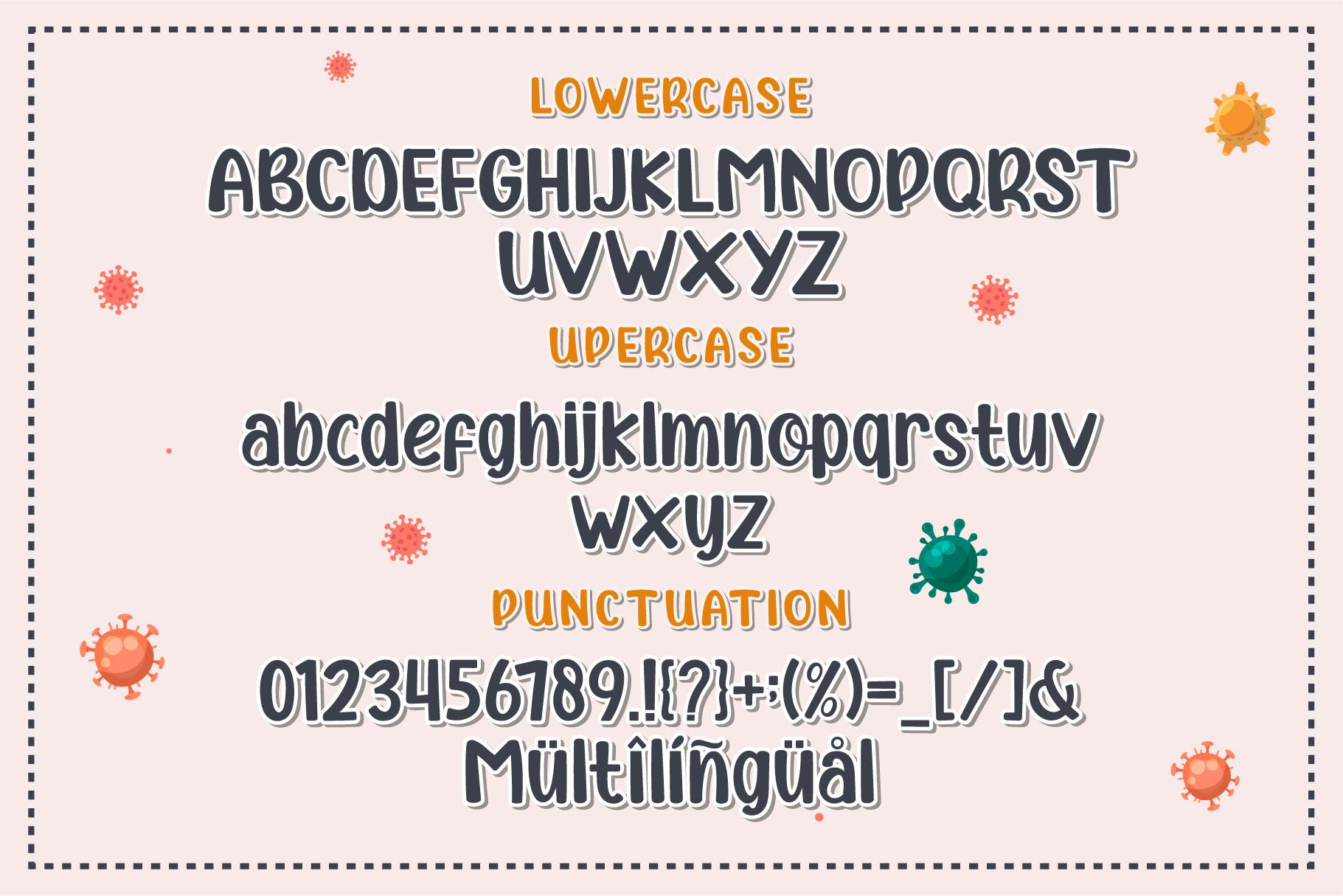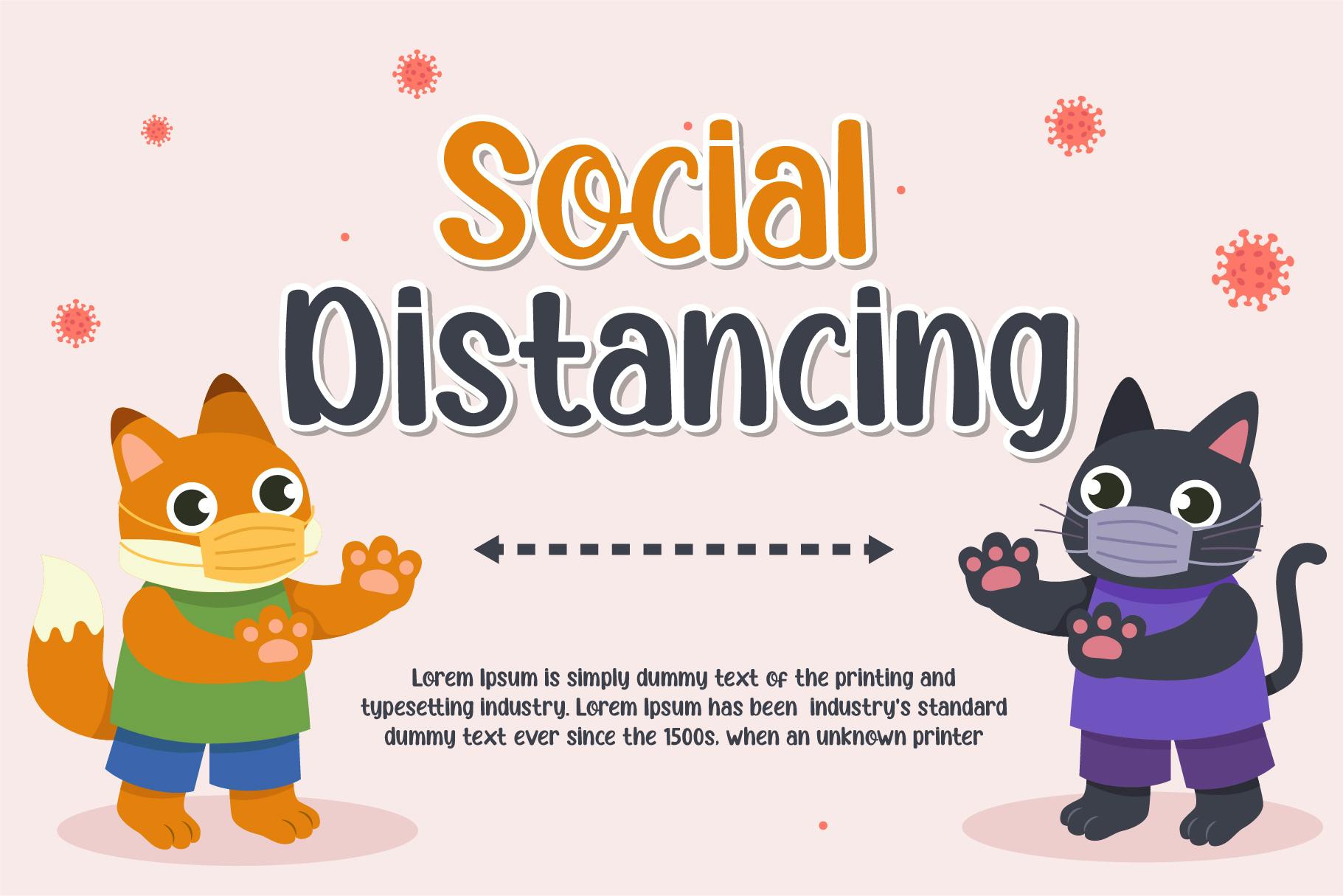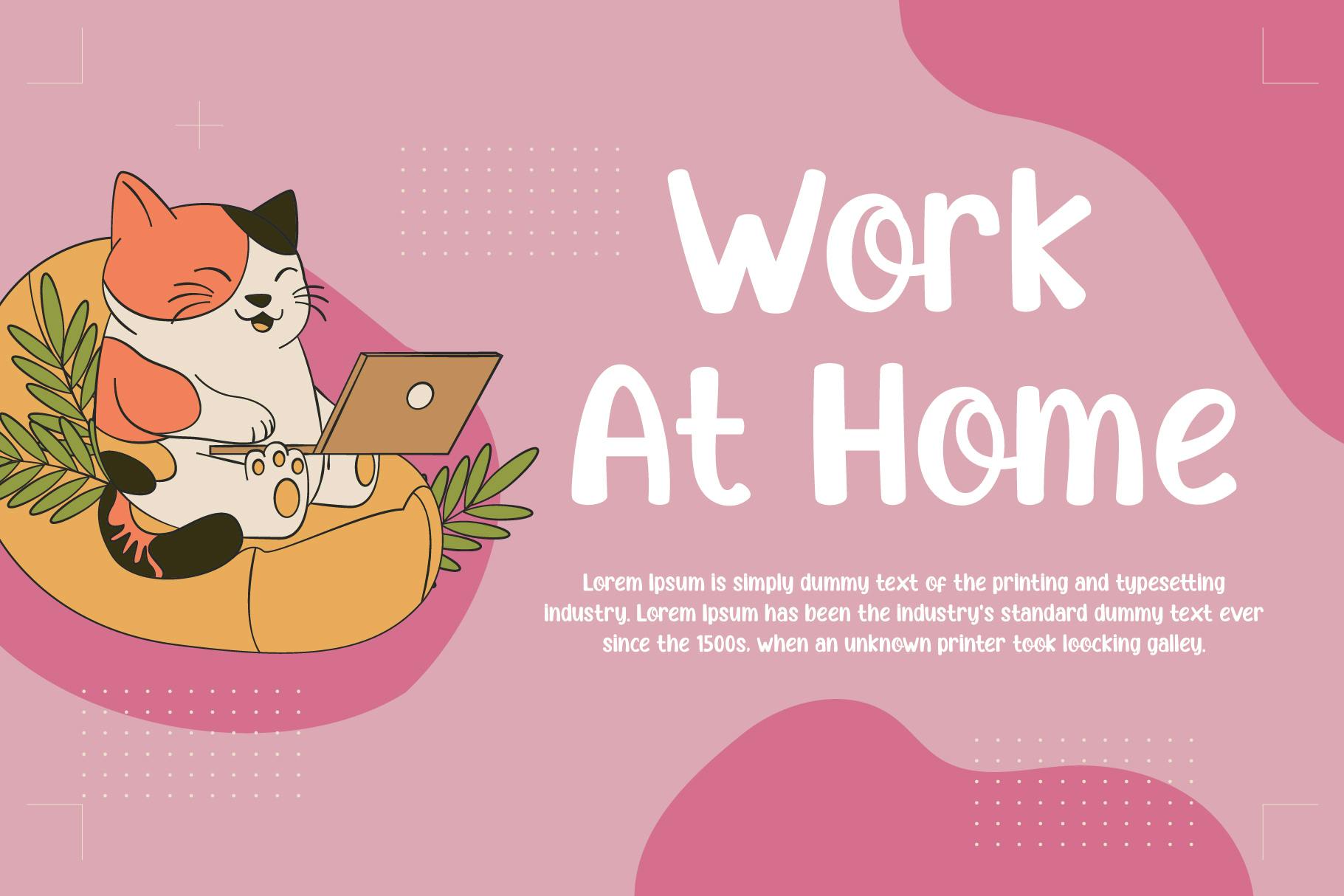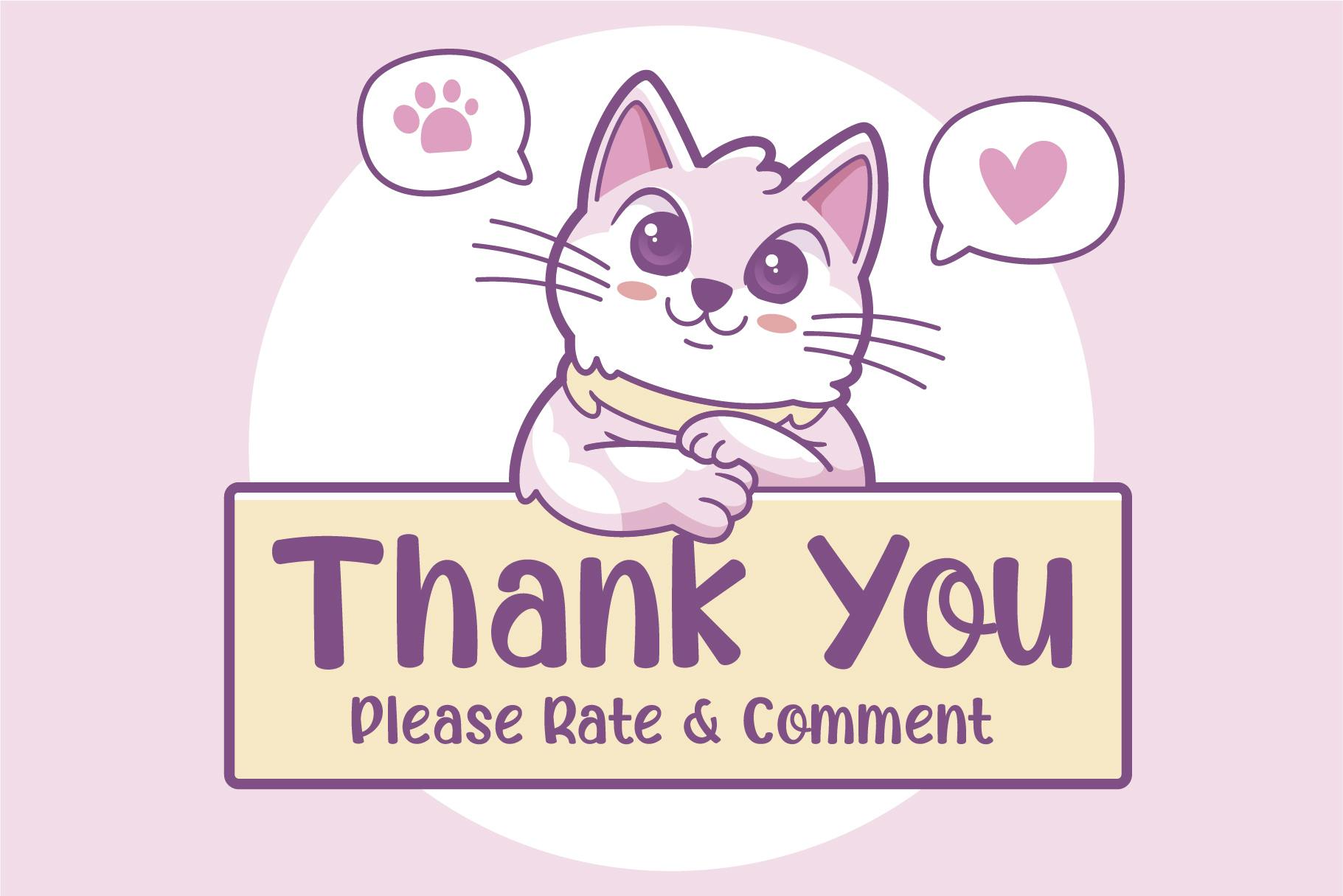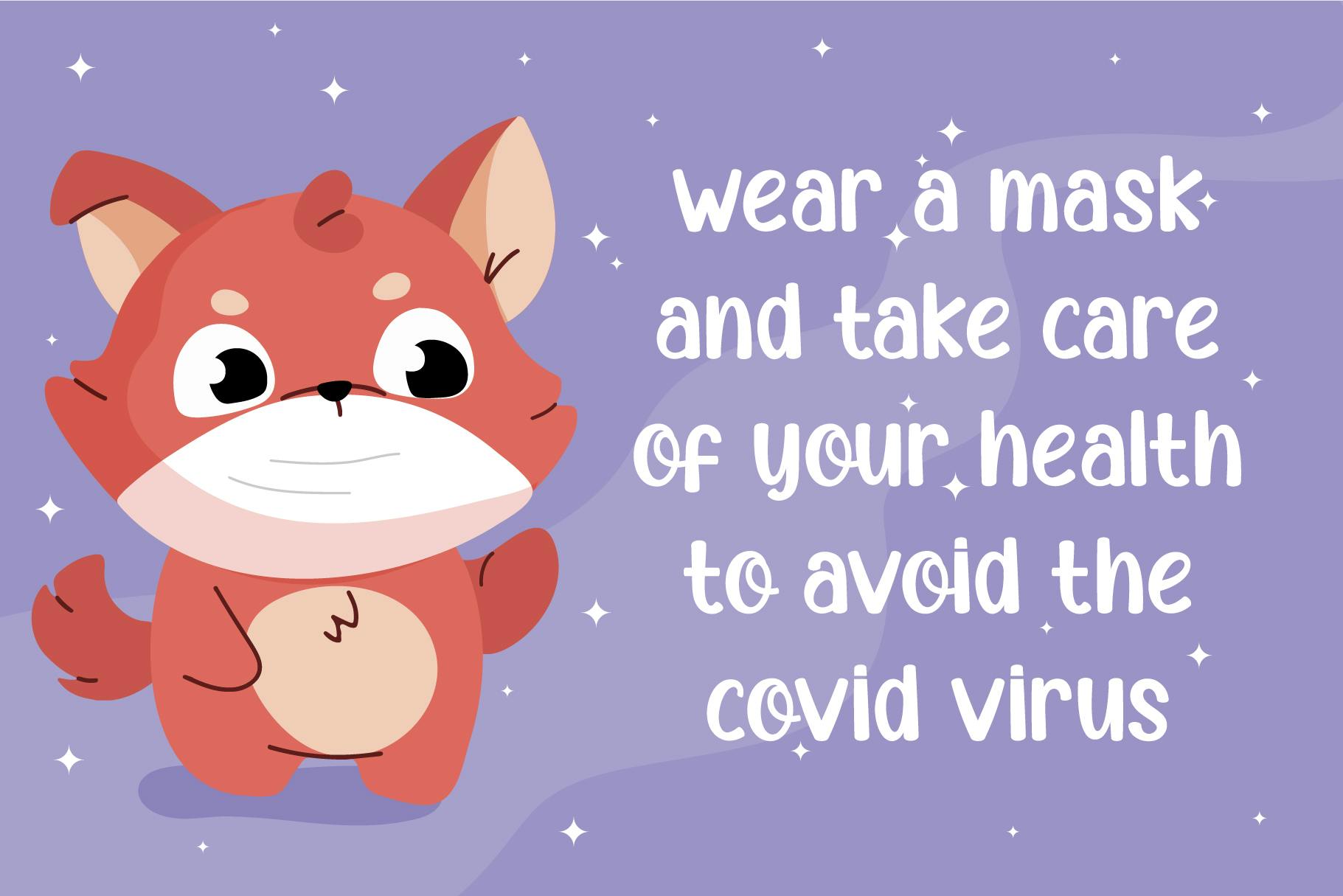
Amoeba Square یک فونت نمایشی است که میتواند برای محصولاتی مانند آموزش بهداشت، بیمارستانها، صنایع دستی، نقل قولهای خندهدار، بستهبندی محصولات، طراحیهای محصولات، هنرمندان، برچسبها، عکاسی، واترمارکها، لوگو و برندینگ مورد استفاده قرار گیرد.